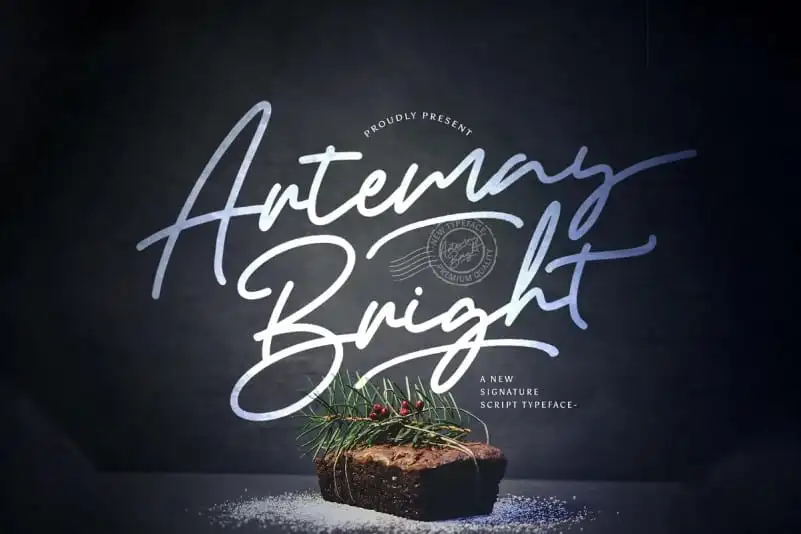
Artemay Bright Handwritten Font – Download Grátis
A Artemay Bright Handwritten Font é uma preciosidade que surgiu dos dedos de StringLabs. Essa Typeface elegante vem para revolucionar a forma como você cria projetos, dando-lhe a oportunidade de fazer sua arte fluir com suavidade e graça em cada letra escrita à mão. Inspirada nas características exuberantes da fonte original, ela é perfeita para aqueles que buscam uma maneira sofisticada de tornar seus designs únicos ainda mais belos e inovadores. Atrai os olhos com seu estilo distintivo, a Artemay Bright Handwritten Font promete transformar qualquer projeto em um trabalho de arte. Seja em anúncios ou letras douradas na capa de uma revista, este é o tipo que vai fazer as pessoas se apaixonarem por suas criações e usar sua beleza para criar designs excepcionais. Com Artemay Bright Handwritten Font, você não precisa de habilidades adicionais para expressar seu design em um nível superior.